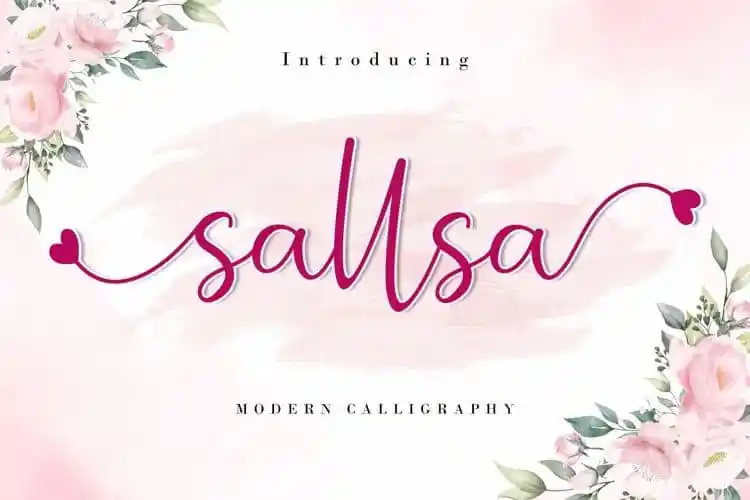
A Sallsa Calligraphy Font é uma bela e moderna fonte escrita a mão que traz à vida um estilo script sofisticado e versátil. Seu aspecto delicado, com seus belos finais de letra (swashes) e ligaduras (ligatures), complementam perfeitamente qualquer projeto design que busque uma sensação natural e autêntica. Desenvolvida pela AEN Creative Studio em 99designs, a fonte ganha vida nas áreas onde se espera uma mão escritora: cartões de convidados para casamentos, cards de agradecimento, citações, cartazes de festas, logotipos e cartões de negócios. A PUA Encoding da fonte facilita a navegação por todos os caracteres e finais de letra (swashes) dentro do design, garantindo uma experiência de uso fluida para designers. Sua delicadeza e elegância fazem com que esta font se destaque em qualquer projeto onde seja necessário adicionar um toque pessoal. Com sua composição moderna e seu charme clássico, a Sallsa Calligraphy Font oferece ao designer uma opção versátil para incorporar elementos de escrita a mão em projetos variados, criando designes elegantes e sofisticados que combinam perfeitamente com o estilo do cliente.